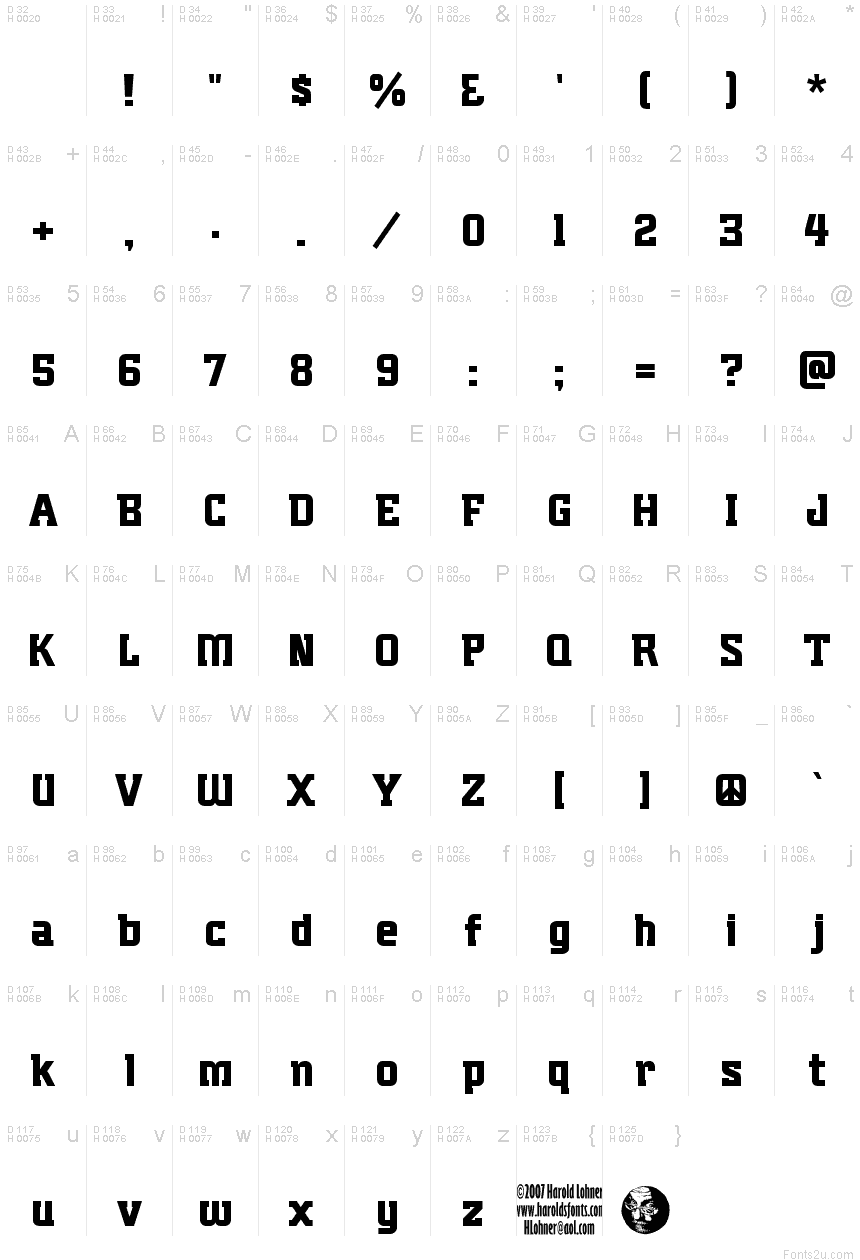
Plumber's Gothic
Plumber's Gothic od Harolda Lohnera je bezplatné průmyslové patkové písmo s jasným nádechem korporátní estetiky poloviny 20. století. Písmo, inspirované návrhy Geralda Stahla and Associates z roku 1960, mění těžké, hranaté tvary na prvky připomínající potrubní konstrukci. Díky tupým rohům, hlubokým zářezům a zaobleným spojům si tento blokový styl zachovává svou dynamiku, aniž by působil strnule.
Hodí se všude tam, kde potřebujete spojit surovou funkčnost s retro vzhledem: v logotypech, nápisech, obalovém designu, titulcích plakátů nebo na obálkách časopisů. Jelikož jde o bezplatné písmo, skvěle vynikne i v úvodních titulcích a krátkých nápisech, kde tyto robustní, do sebe zapadající znaky dodávají i pár písmenům vzhled starých štítků a dílenských emblémů.